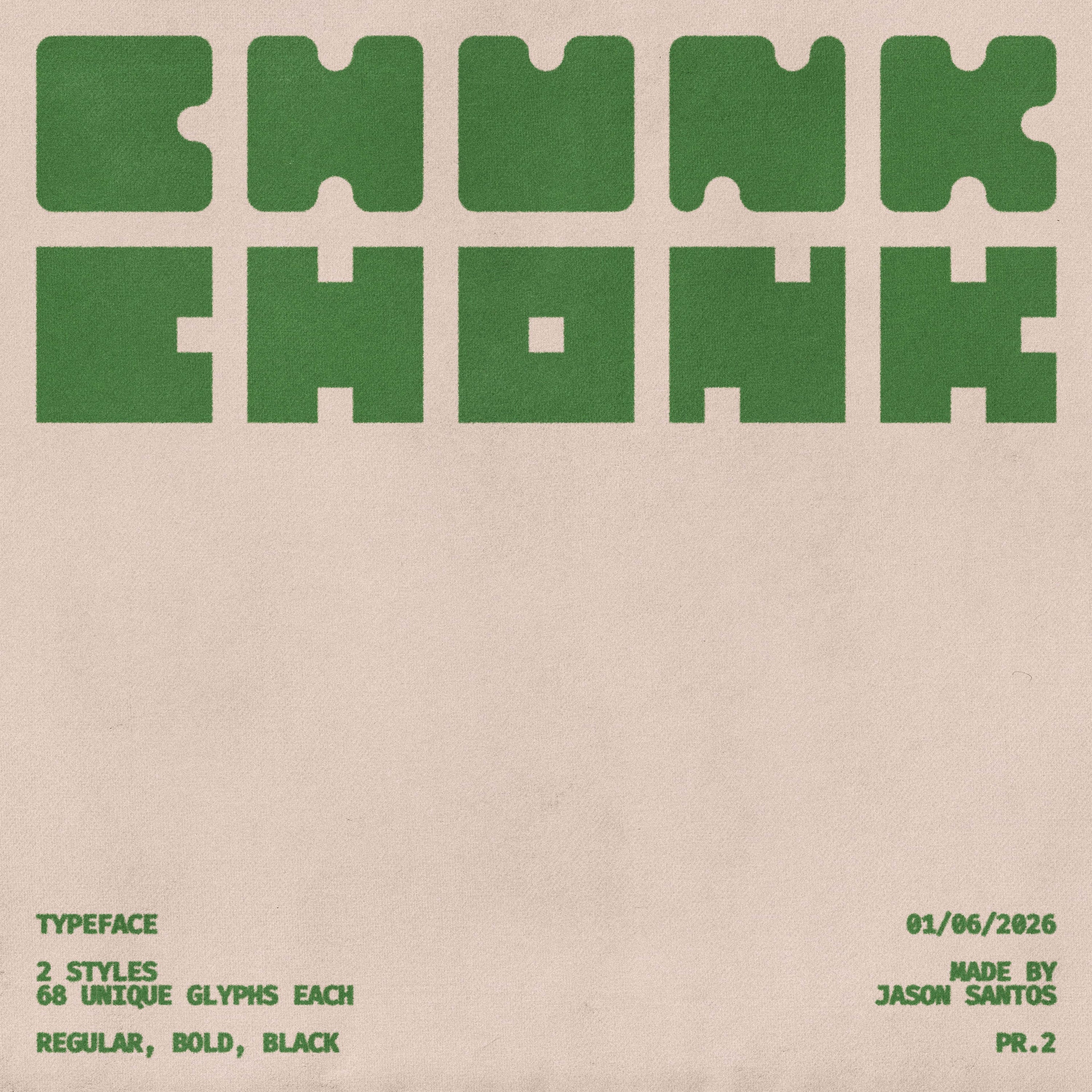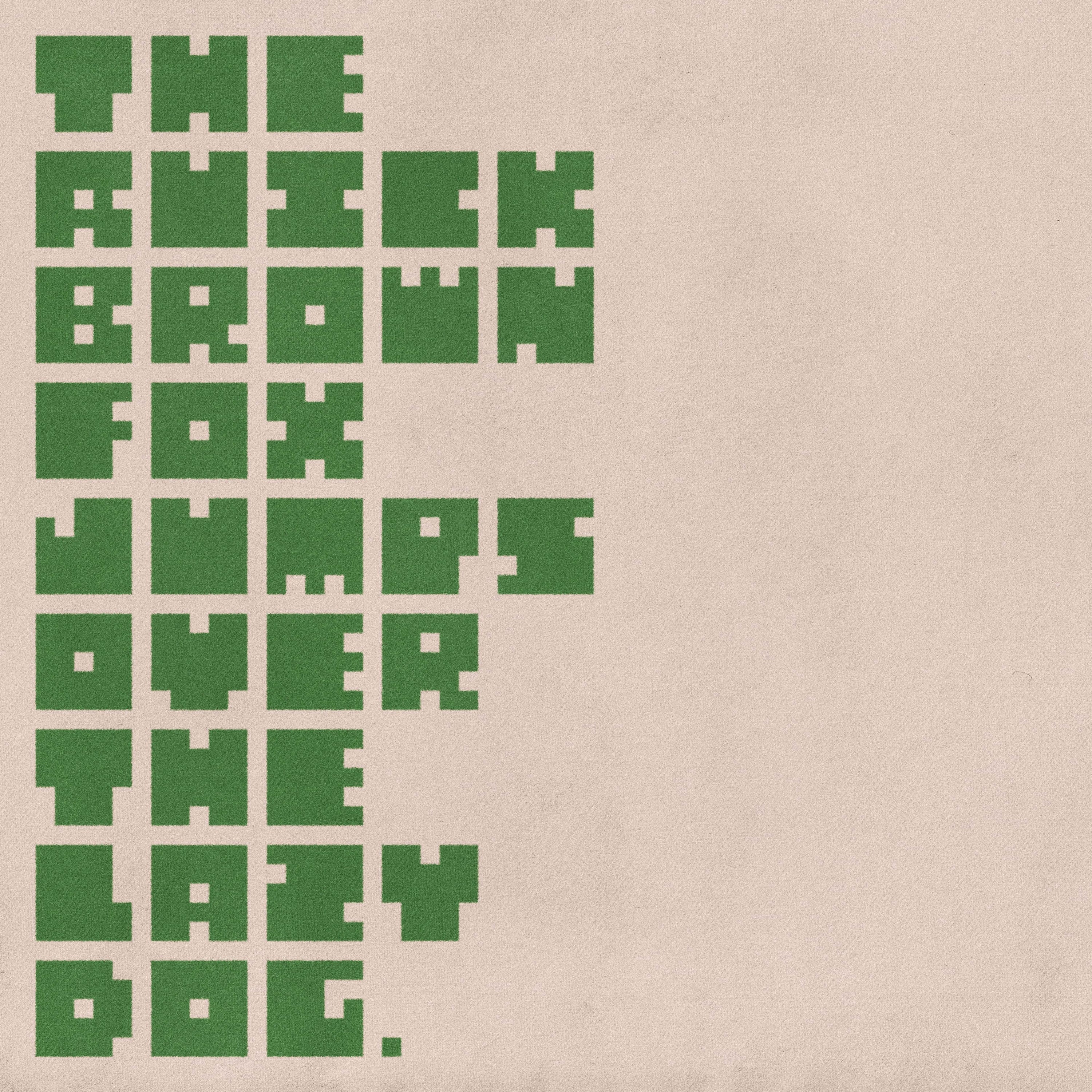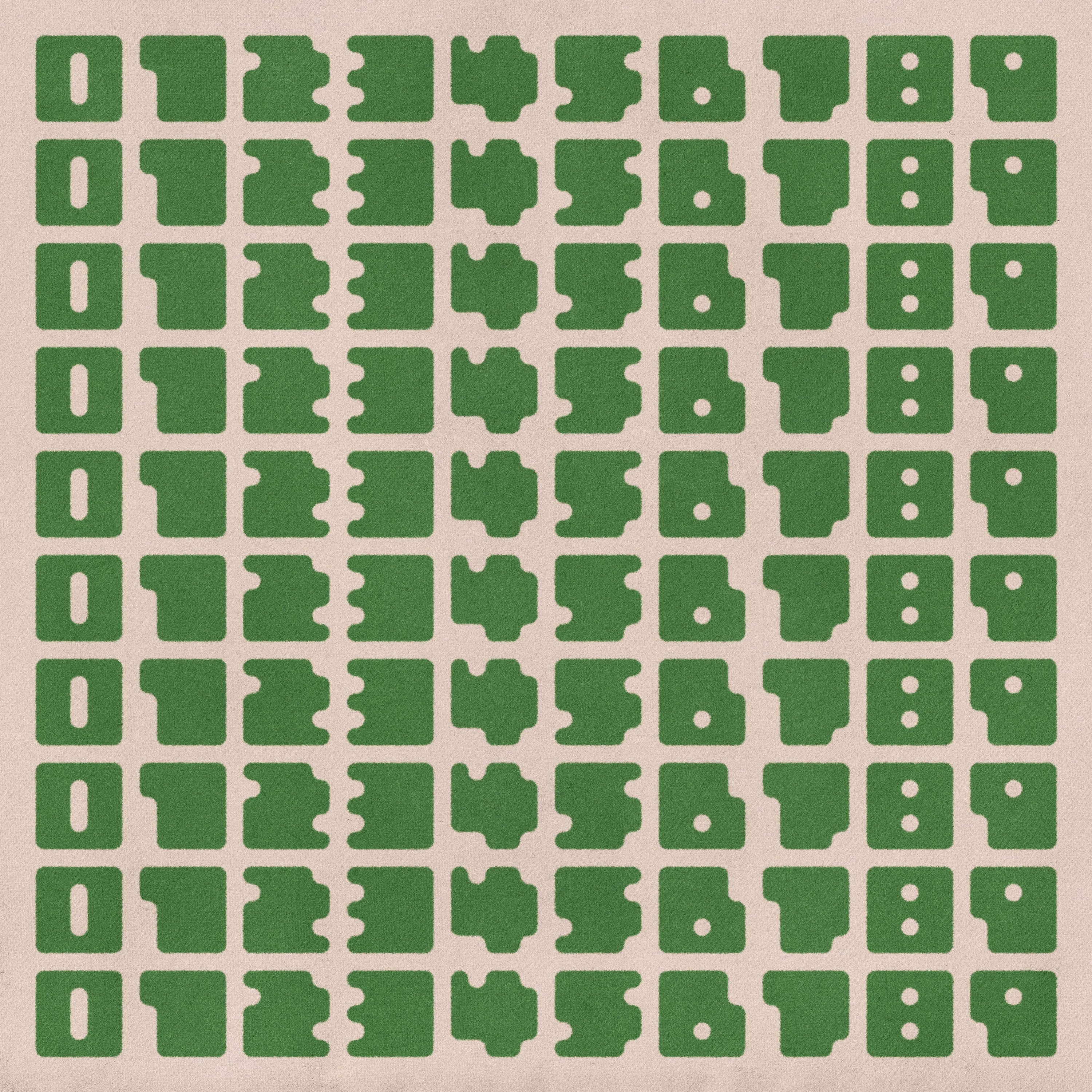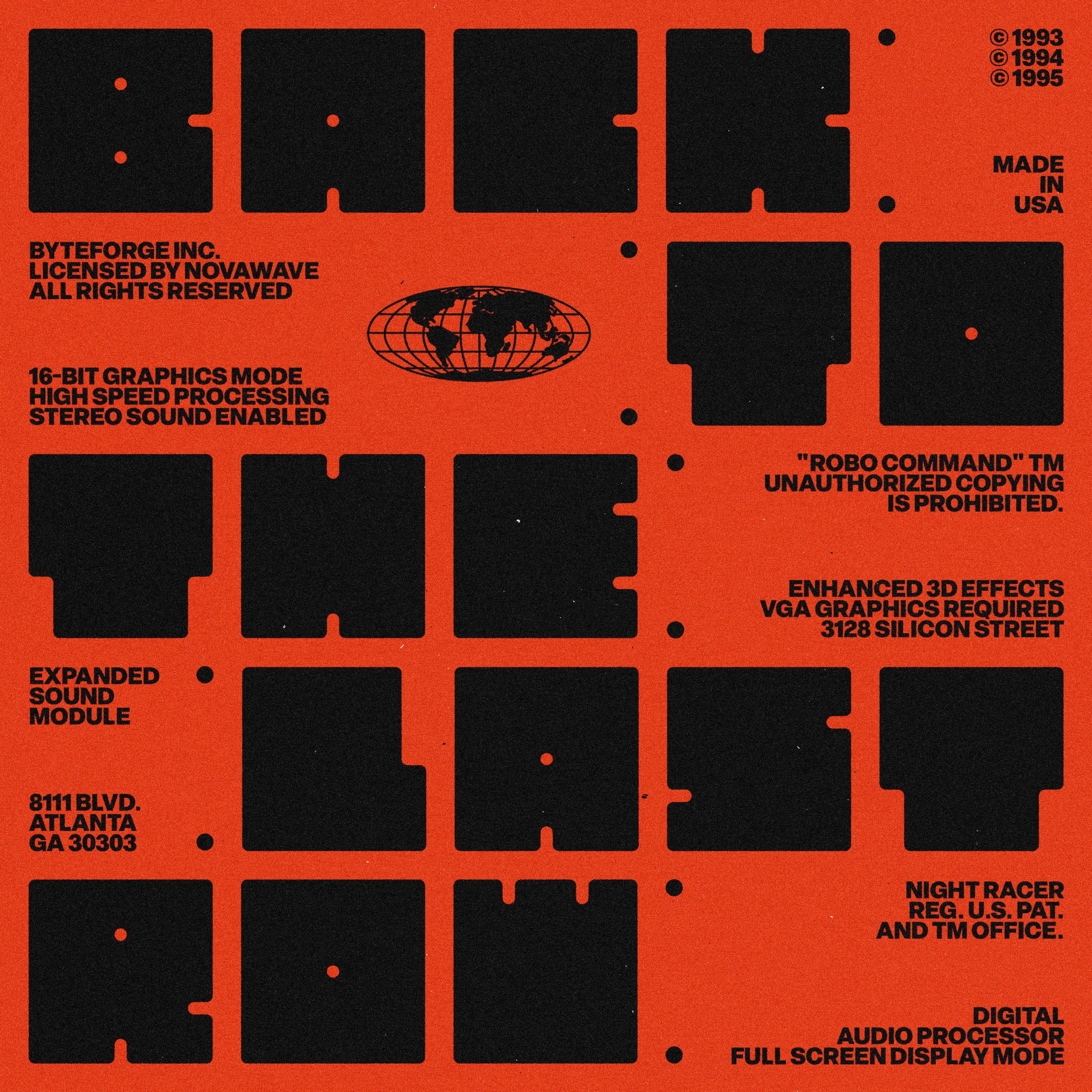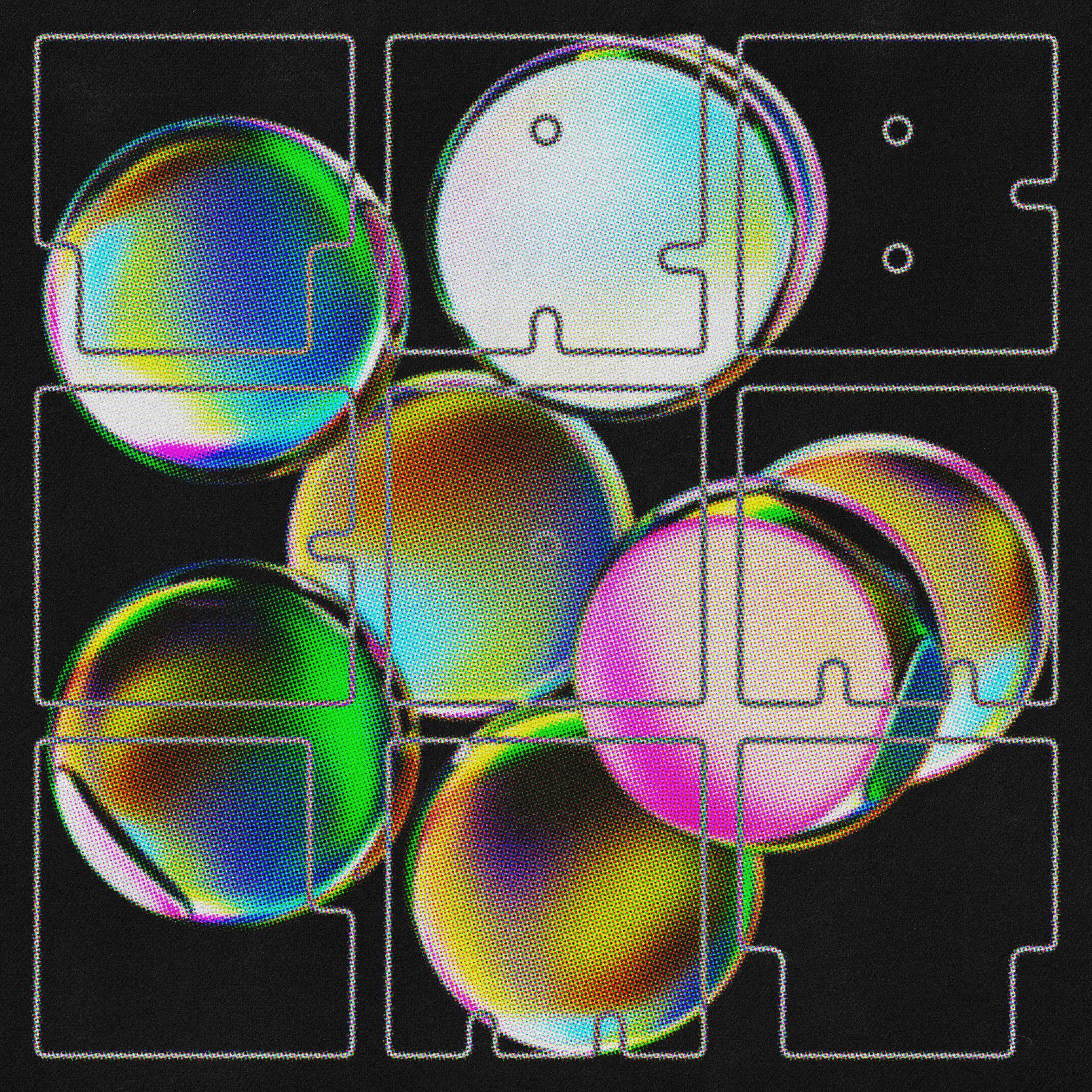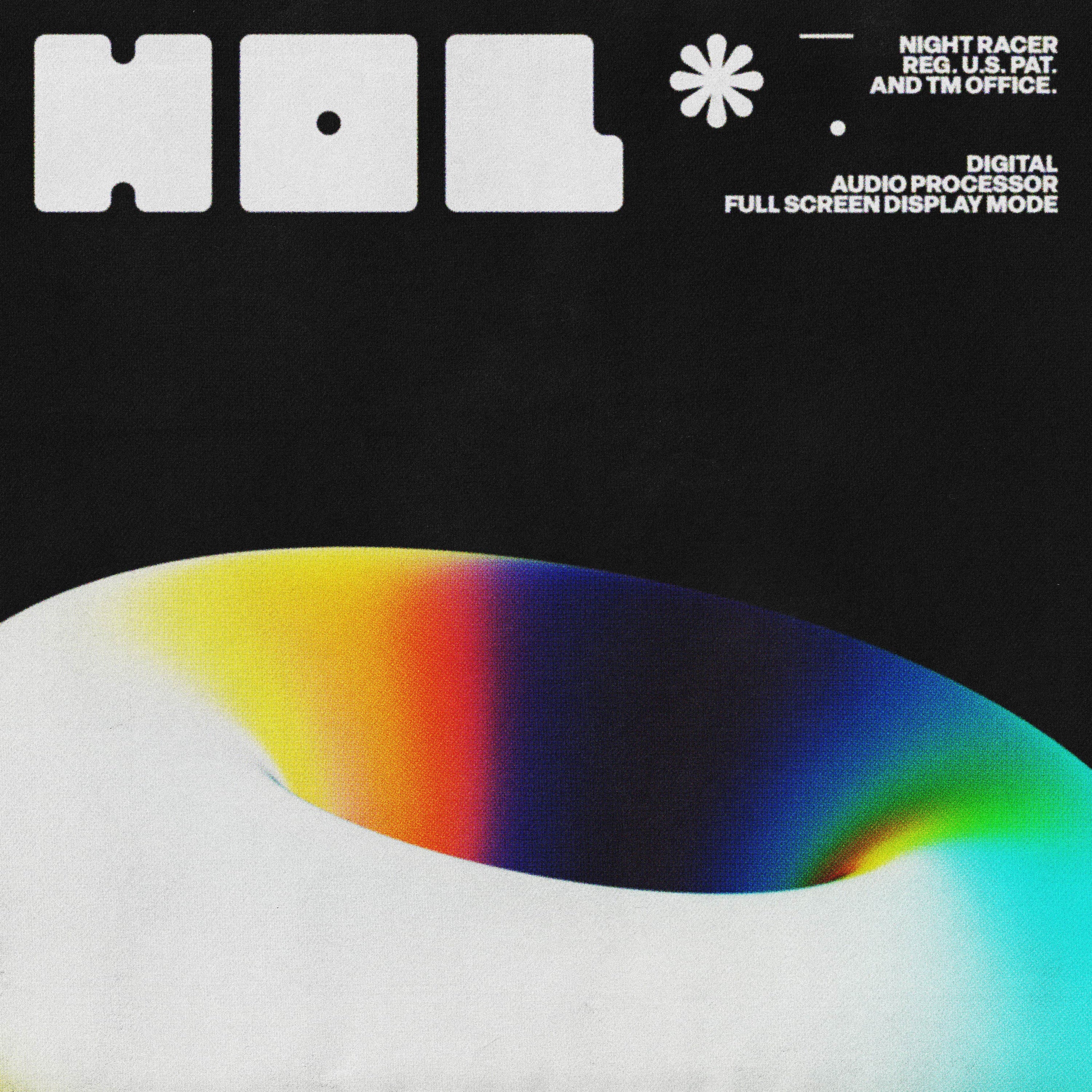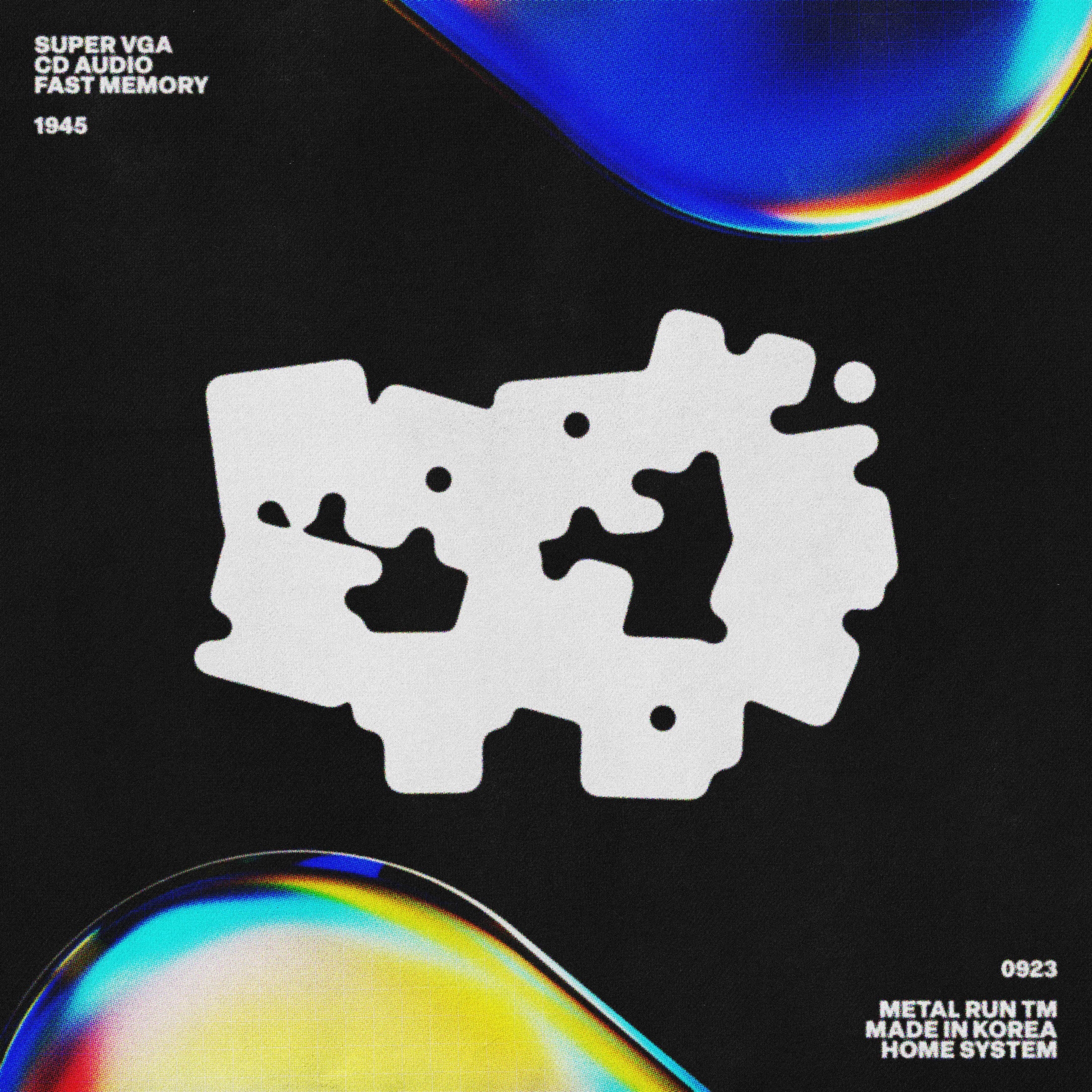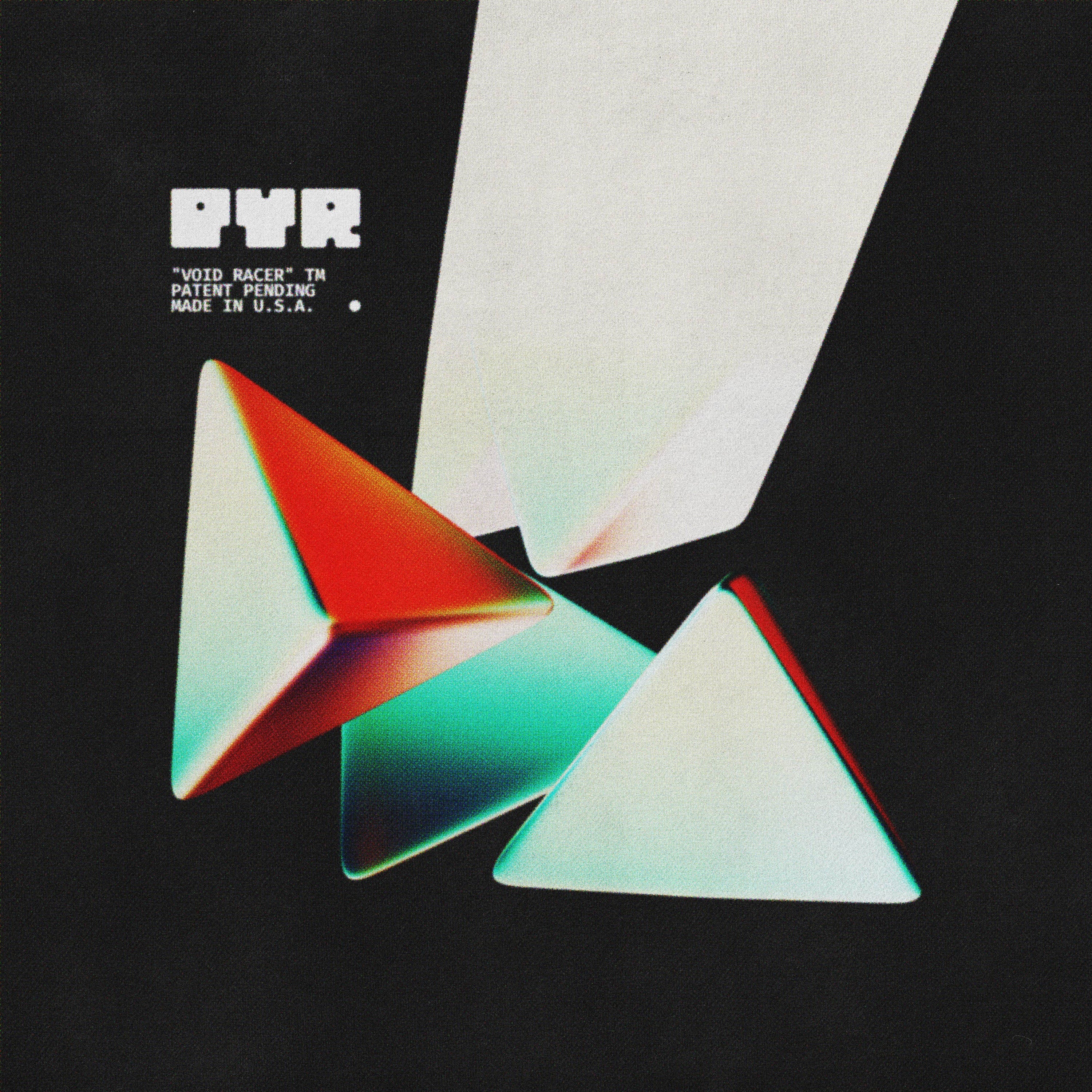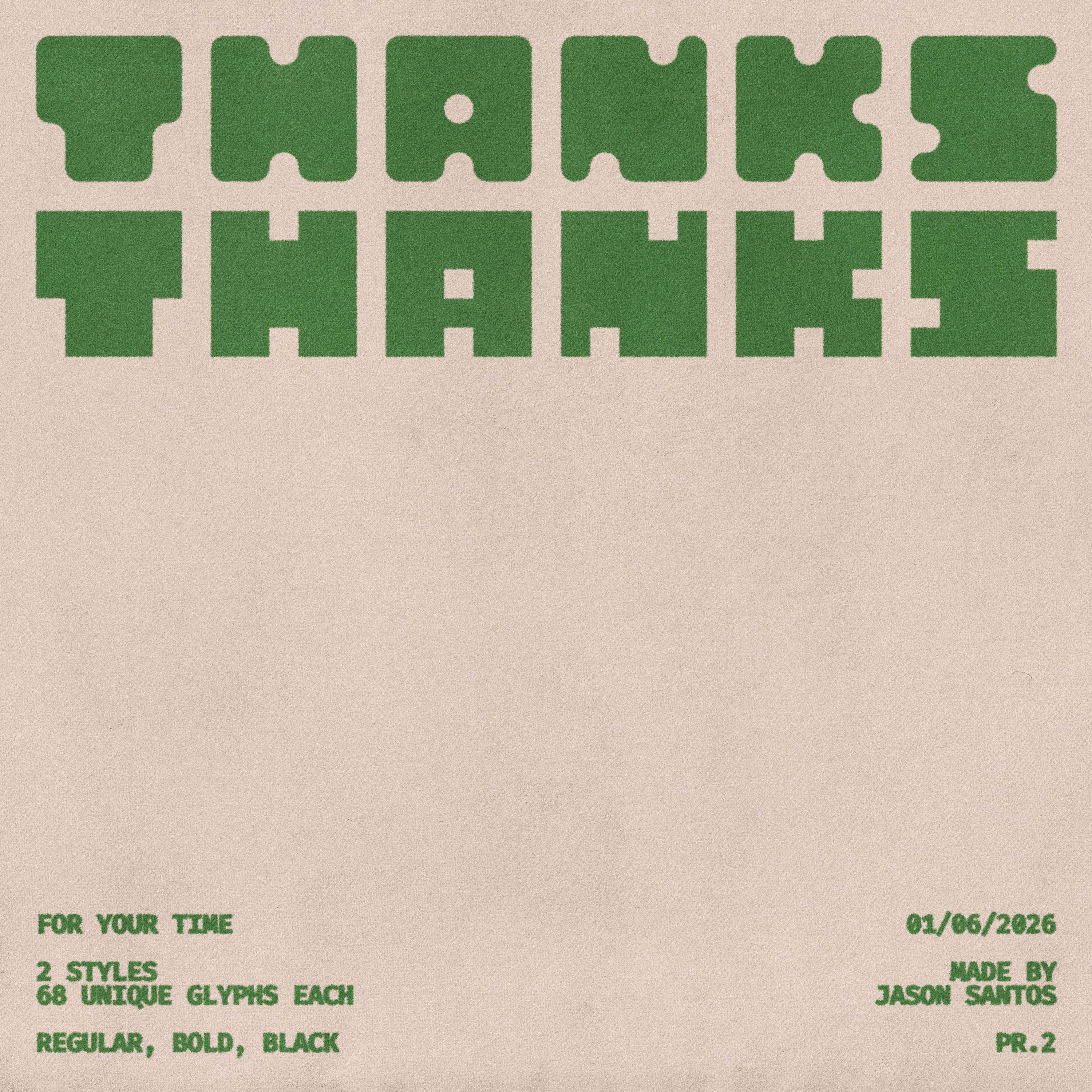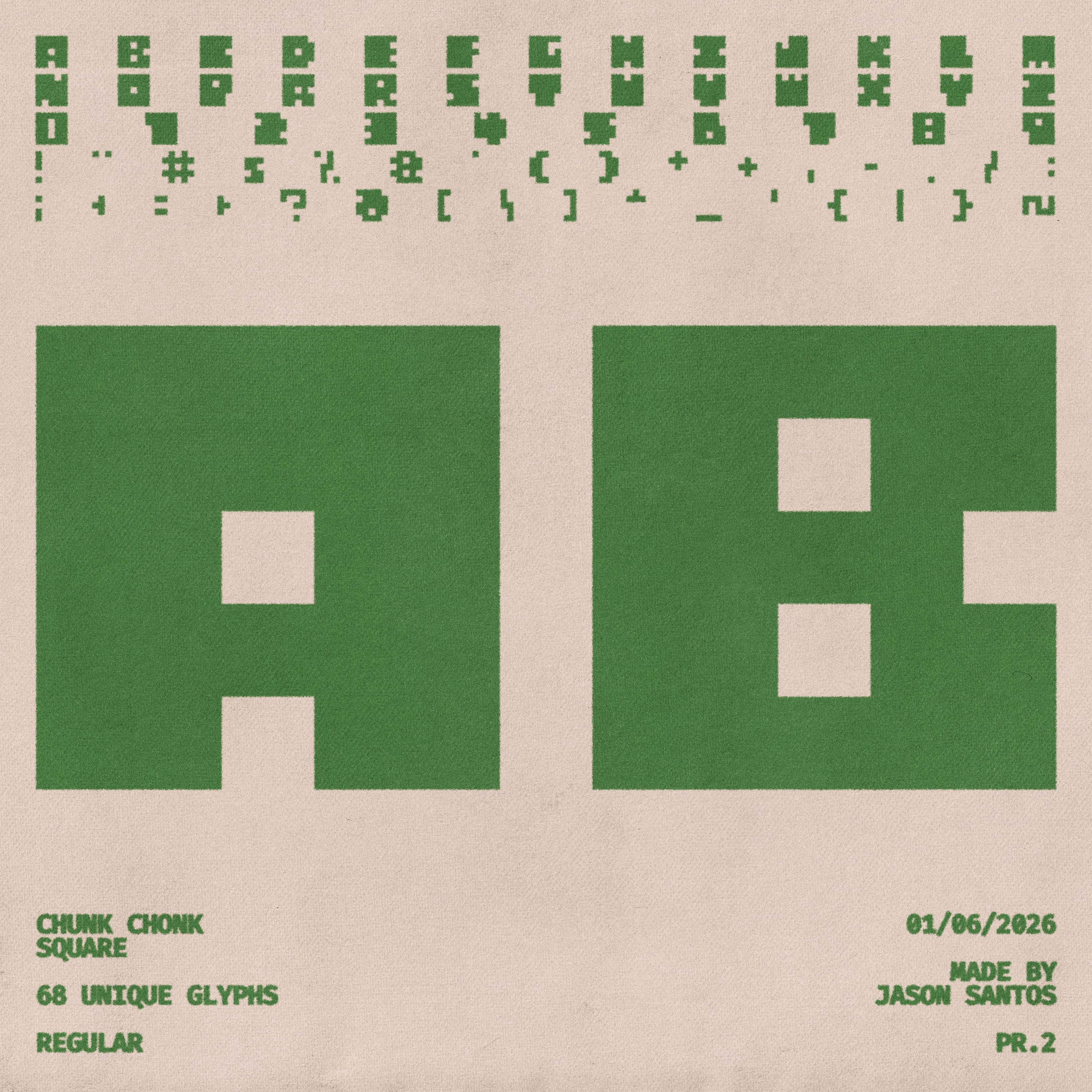
Tipografía Chunk Chonk
Chunk Chonk es una tipografía de exhibición brutalista y pesada, creada para lograr el máximo impacto. Con formas de letras ultragrosas y potentes estructuras de bloque, crea una presencia audaz diseñada para dominar cualquier composición.
Disponible en estilos Square y Round, Chunk Chonk combina una geometría rígida con curvas más suaves, ofreciendo flexibilidad a los diseñadores sin renunciar a su inconfundible peso visual. Está pensada para proyectos en los que la tipografía debe transmitir fuerza, confianza y ser reconocible al instante.
Perfecta para logotipos, marcas de moda urbana, carteles, embalajes, merchandising, titulares y sistemas de identidad audaces.
Características
• 68 glifos
• 6 estilos (Square Regular, Square Bold, Square Black, Round Regular, Round Bold, Round Black)
• Mayúsculas
• Números
• Puntuación
• Símbolos
• Matemáticas